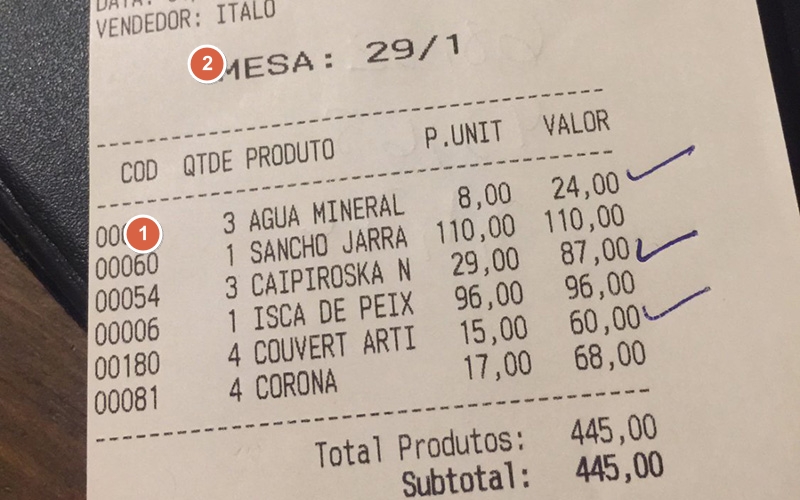
⤴ Foto original da amostra. As fontes usadas na amostra: ❶fonteZ2-largo ❷fonteZ2
Fonte de cupom fiscal, tipografia de fatura simplificada, fonte de impressora térmica recibo, tipografia de nota fiscal